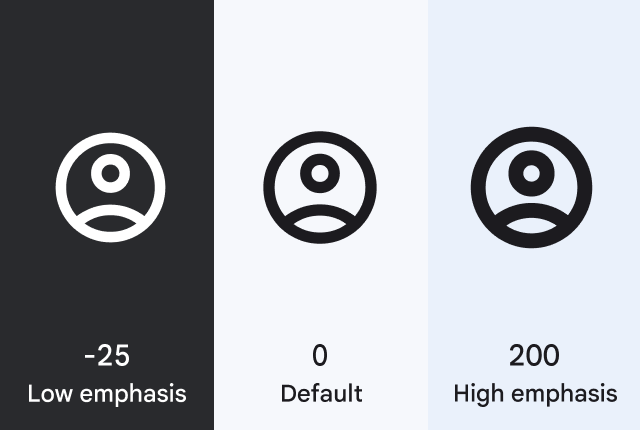
מהם סמלי חומרים?
סמלי Material הם הסמלים החדשים ביותר שלנו, עם יותר מ-2,500 גליפים בקובץ גופן אחד עם מגוון רחב של וריאנטים של עיצוב. הסמלים זמינים בשלושה סגנונות ובארבעה צירים של גופן משתנה שניתן לשנות (מילוי, עובי, דרגה וגודל אופטי). ראה את הקבוצה המלאה של סמלי חומרים בסמלים של Materials ספרייה.
ציר FILL
בעזרת מילוי אפשר לשנות את סגנון ברירת המחדל של הסמל. סמל יחיד יכול להציג גם מצב לא מלא וגם מצב מלא.
כדי להעביר מעבר בין מצבים, משתמשים בציר המילוי לצורך אנימציה או אינטראקציה. הערכים הם 0 לברירת המחדל או 1 למילוי מלא. יחד עם ציר המשקל, גם המילוי משפיע על המראה של הסמל.
ציר wght
משקל מגדיר את עובי הקו של הסמל, עם טווח משקלים בין דק (100) למודגש (700). המשקל יכול להשפיע גם על הגודל הכולל של הסמל.
ציר GRAD
המשקל והדירוג משפיעים על עובי הסמל. שינויים בציון הם מפורטים יותר משינויים במשקל, והם משפיעים במידה קטנה על גודל הסמל.
אפשר להשתמש ב'ציון' גם בגופנים מסוימים של טקסט. אפשר להתאים את רמות הכיתות של הטקסט והסמלים כדי ליצור אפקט חזותי הרמוני. לדוגמה, אם לעיצוב הטקסט יש ערך ציון של -25, הסמלים יכולים להתאים לו ערך מתאים, למשל -25.
אפשר להשתמש בציון לצרכים שונים:
הדגשה נמוכה (למשל: -25 בדרגה): כדי להפחית את הברק של סמל בהיר על סמל כהה השתמש בציון נמוך.
הדגשה גבוהה (למשל, 200 בדרגה): כדי להדגיש סמל, מגדילים את הערך החיובי. בלי ציון.
ציר opsz
הגדלים האופטיים נעים בין 20dp ל-48dp.
כדי שהתמונה תיראה זהה בגדלים שונים, עובי הקו (עובי) משתנה כשגודל הסמל משתנה. גודל אופטי מאפשר לך אפשר לשנות את עובי הקו כשמגדילים או מקטינים את הסמל.